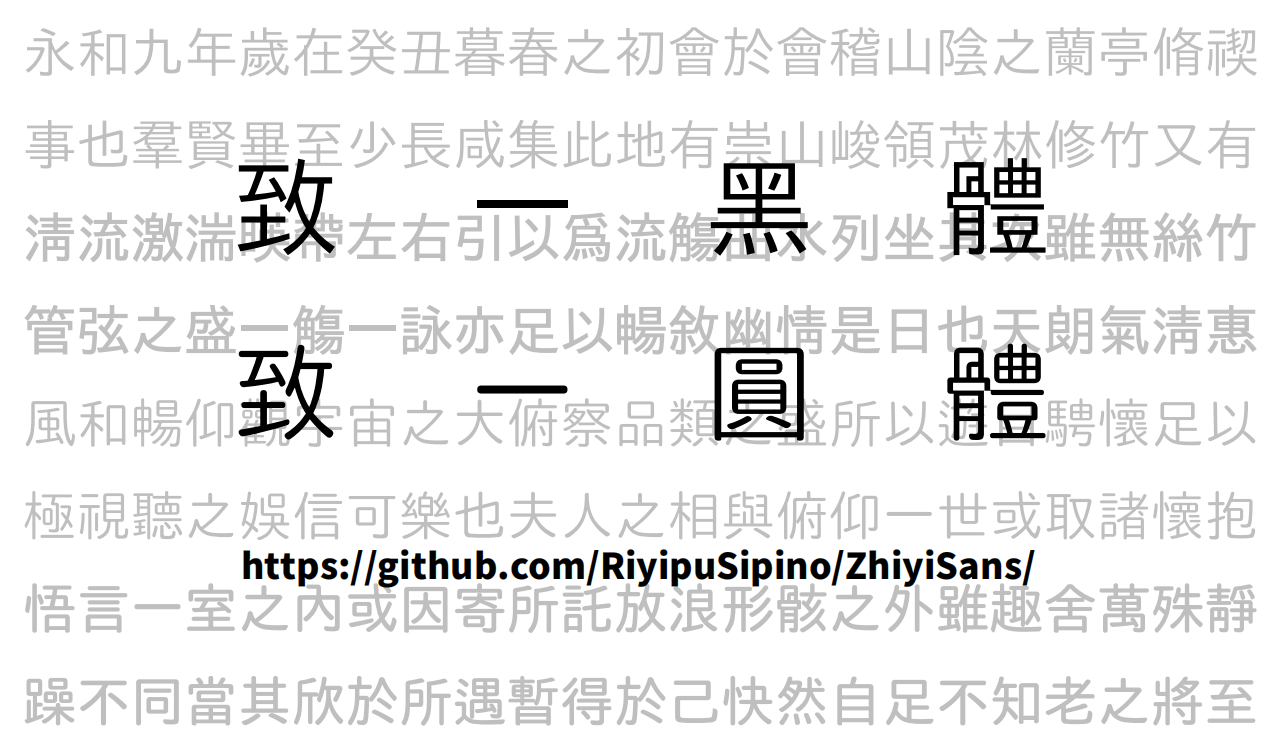
致一圆体 ZhiyiMaru 致一圓體_傳承形
虽然世界各不相同,但人们的情感却是一致的。——《兰亭集序》
“致一圆体”是一系列采用真迹字体格式封装的 OpenType 字体,这些字体遵循 Unicode 编码标准。该系列字体基于旧印刷字体“霞鶩晰黑”进行改进,并推出了粗体、圆体以及粗圆体版本,以满足现代阅读环境中对多种样式和不同字重需求的要求。
预计该字体将分为两种版本:一种为“传承形”,另一种为“致一形”。其中,“致一形”版本采用了与“致一宋体”相同的字形,目前仍在开发过程中。
正如人们所说:“字的形态会不断演变,发音也会发生变化。”从古至今,字形的演变就像潮汐的起伏一样,是一种自然而然的规律。在可能的情况下,我们会按照字理来区分字形,当然,这背后还是追求一种逻辑性。不过,字形的演变本身也是一种逻辑性的体现。因此,本项目开发了“致一黑体/圆体”这一传承性字形版本。我们采用了完全基于旧印刷字形的设计,保留了字形的传统风貌,只对少数部件进行了修改,以遵循统一的规则——即同一个字形部件在不同语境下的书写方式尽可能保持一致,而不再过分强调字理上的差异。
字形修改
- 所有的部件都将被改为“曰/日”这个名称,这与“朱”和“替”等部件的名称保持一致。
- 在蔑部件的下方部分,横线和斜线相互交叉,这样就能避免“蔑的下半部分看起来像‘伐’字,但实际上却更像‘戍’字”的情况发生。
- 巷根据字理改从㔾
- 邦字的第一个“撇”改为横,与其他从丰之字保持一致,从而与丯(契、害所从)区分开来。
- 天改为第二横长,忝、吞等部件统一来自天
- 在右上角,根据字形规则,将其改成了“羊角头”字样。